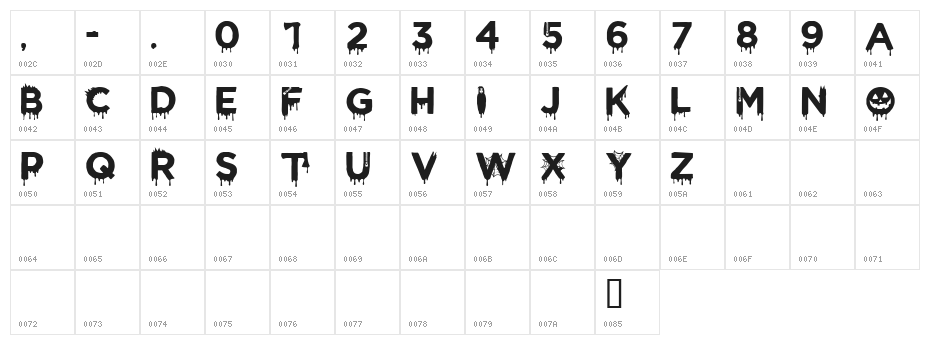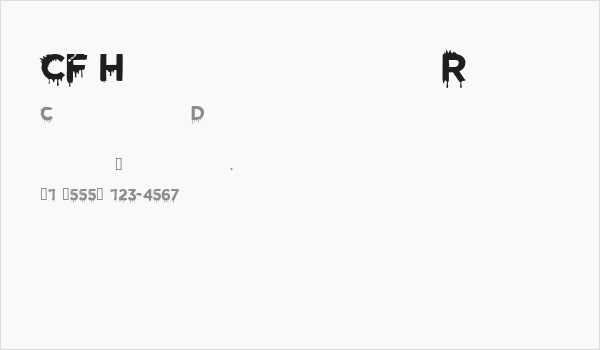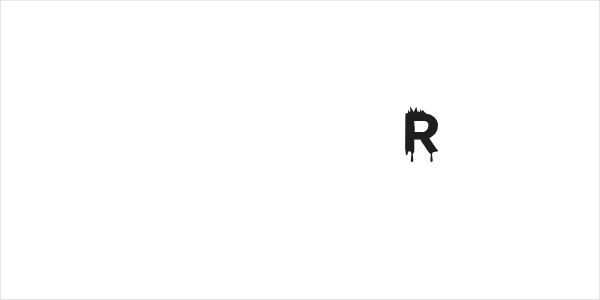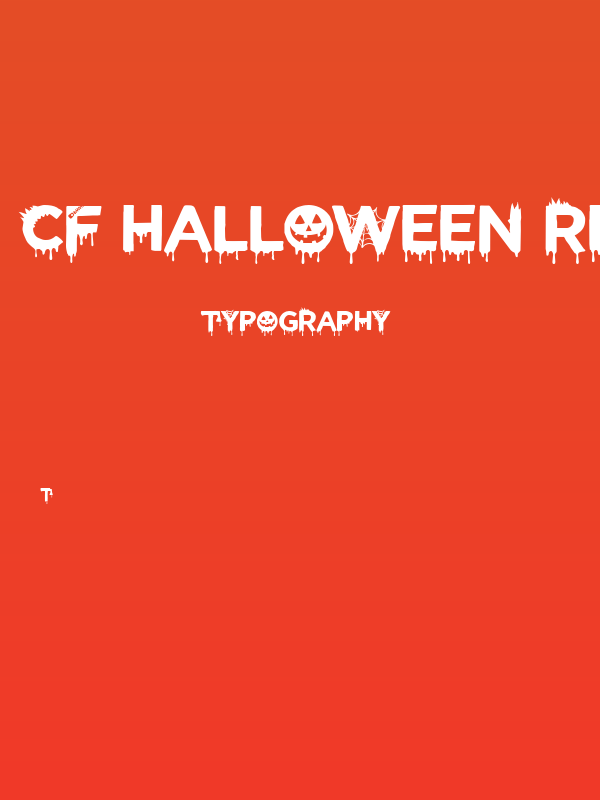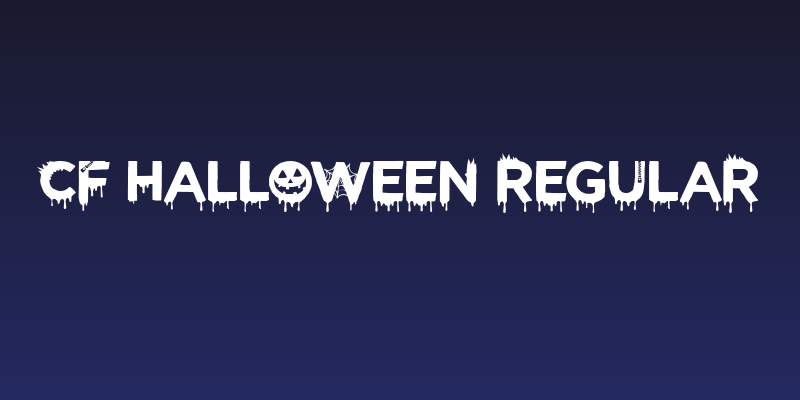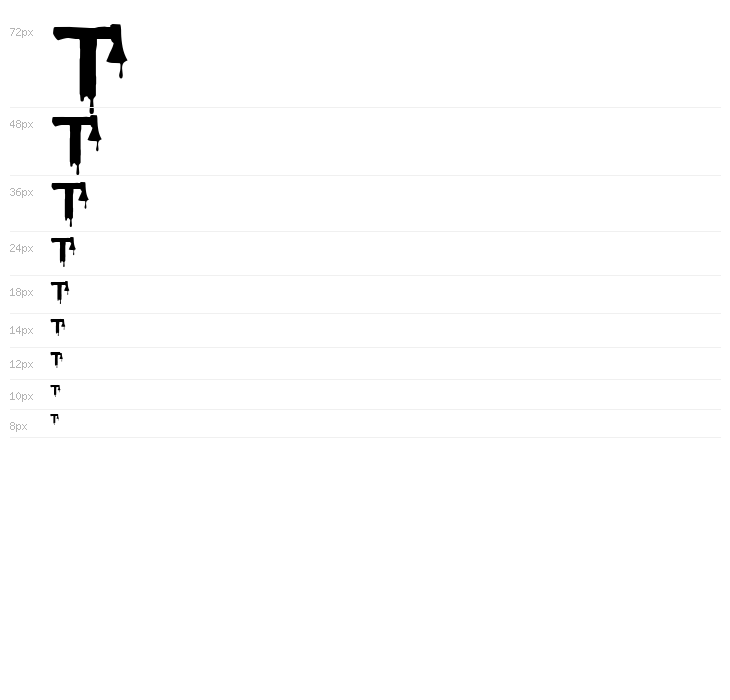
CF Halloween Regular Font
| Progetti proposti | Ideal for Halloween invitations, event posters, themed party decorations, and spooky merchandise designs. |